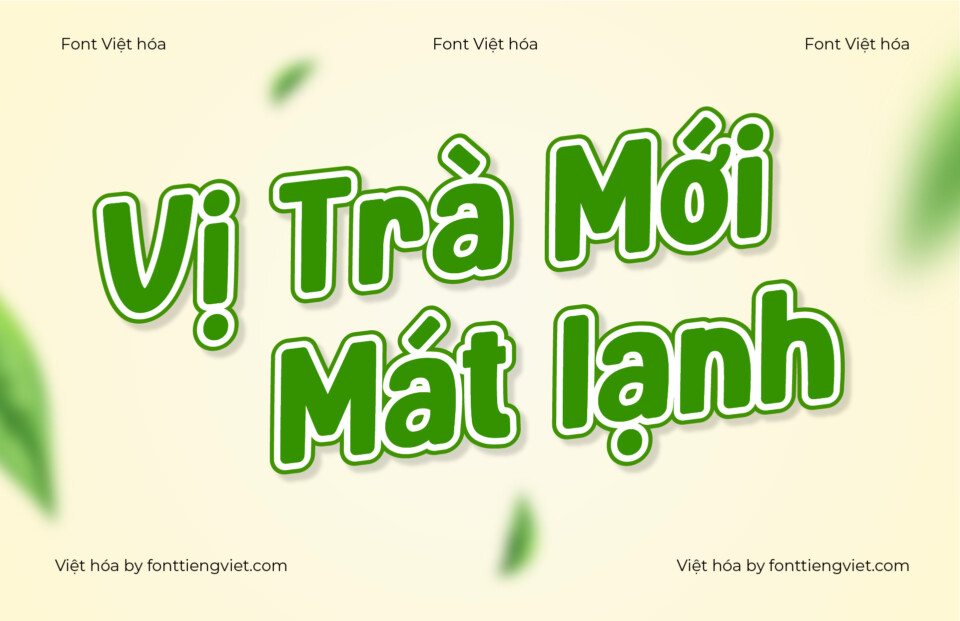
Font Việt hóa 1FTV VIP Milk Kids
Font Việt hóa 1FTV VIP Milk Kids – Bộ Font Hoạt Hình Đáng Yêu Cho Bé
Giới thiệu về bộ Font Việt hóa 1FTV VIP Milk Kids
Trong thiết kế đồ họa dành cho lứa tuổi thiếu nhi, việc lựa chọn một Font Miễn Phí phù hợp đóng vai trò then chốt để truyền tải sự vui nhộn. Font Việt hóa 1FTV VIP Milk Kids chính là giải pháp hoàn hảo với phong cách chữ bo tròn, nét dày và mang đậm hơi thở của những hộp sữa ngọt ngào. Đây là bộ font được tinh chỉnh kỹ lưỡng về bảng mã Telex, giúp các thầy cô và phụ huynh dễ dàng tạo ra những tài liệu học tập sinh động mà không lo lỗi hiển thị tiếng Việt.
Ưu điểm nổi bật của Font Việt hóa 1FTV VIP Milk Kids
Đặc điểm nổi bật nhất của bộ chữ này là sự thân thiện và gần gũi. Các nét chữ được thiết kế mô phỏng theo nét vẽ tay của trẻ nhỏ, tạo cảm giác mềm mại và tự nhiên. Font Việt hóa 1FTV VIP Milk Kids cực kỳ phù hợp cho các tiêu đề sách truyện, bảng tên lớp học hoặc các video hoạt hình sáng tạo. Nhờ tính ứng dụng cao, bộ font này giúp các sản phẩm thiết kế trở nên nổi bật và thu hút thị giác của các bé ngay từ cái nhìn đầu tiên.
Cách ứng dụng Font Việt hóa 1FTV VIP Milk Kids trong giáo dục
Giáo viên có thể sử dụng bộ font này để thiết kế các slide bài giảng PowerPoint thêm phần hấp dẫn. Việc kết hợp màu sắc tươi sáng cùng các ký tự ngộ nghĩnh sẽ kích thích sự tò mò và niềm yêu thích học tập của học sinh. Ngoài ra, các nhà thiết kế cũng thường ưu tiên lựa chọn bộ chữ này cho các ấn phẩm quảng cáo sữa, bánh kẹo hoặc đồ chơi trẻ em tại thị trường Việt Nam.